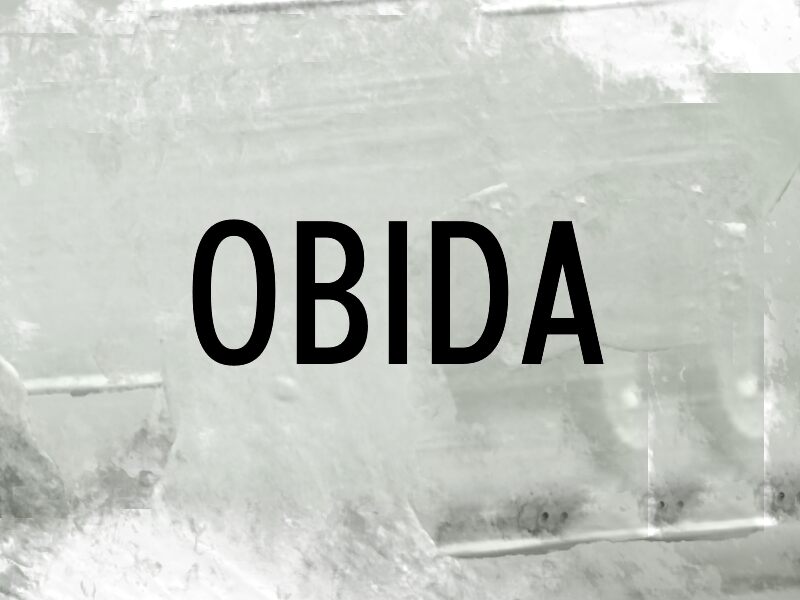
OBIDA
Obida od Wep je bezplatné, zúžené bezpätkové písmo s výrazným, plakátovým rytmom. Písmená pôsobia vysokým a úzkym dojmom, s nekompromisným vertikálnym ťahom a čistými krivkami, ktoré dávajú abecede rázný, mestský hlas, namiesto mäkkého geometrického poňatia.
Vďaka tomu sa tento bezplatný font prirodzene hodí pre hudobné letáky, módne lookbooky, filmové titulky, titulky časopisov a ostré typografické značky, kde krátky text vyžaduje úzky, dominantný tvar. Dobre funguje aj pre monogramy a iniciály, pretože veľké písmená majú silnú siluetu a udržiavajú si svoj dopad, aj keď je text veľmi stručný.